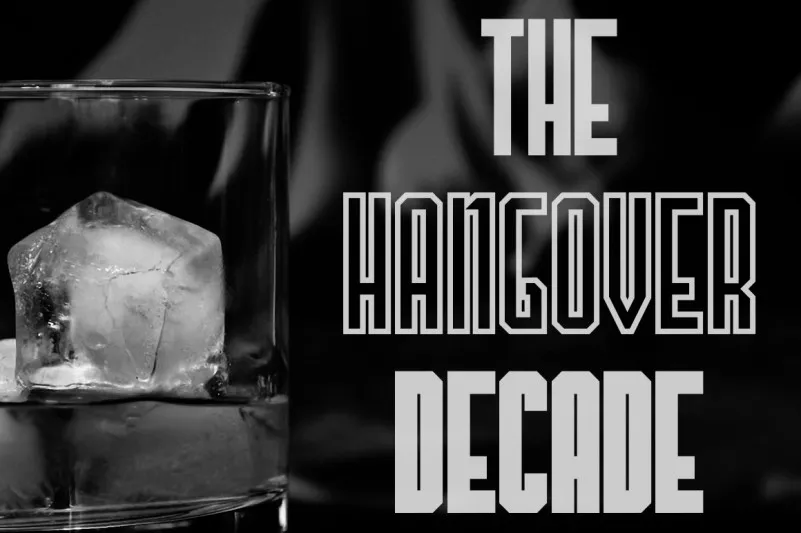
A ‘The Hangover Decade Font’ é uma opção de tipo que se adequa perfeitamente para qualquer projeto onde você deseja dar um toque único e vibrante à sua publicação, desde camisetas até posters ambiciosos. Esta fonte tem sido um destaque em criações digitais ao longo dos últimos anos, especialmente por suas linhas dinâmicas e cores vibrantes. Para designers que buscam algo de uma linguagem mais casual e divertida, essa fonte é certamente a escolha ideal. A ‘The Hangover Decade Font’ não se limita apenas à moda ou marketing; ela também foi bem-sucedida em criações para anúncios no YouTube, materiais promocionais ou até mesmo em campanhas publicitárias. Não perca esta oportunidade de deixar sua marca com um estilo único e moderno. Aqui está uma fonte certamente digna de ser adquirida – é gratuita para uso comercial e os donativos são muito apreciados! Você pode fazer seu doação através de PayPal no link fornecido.